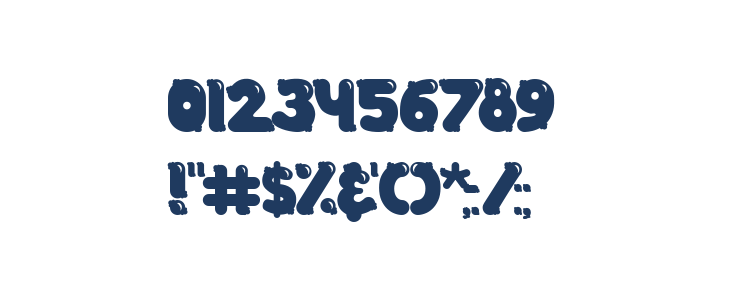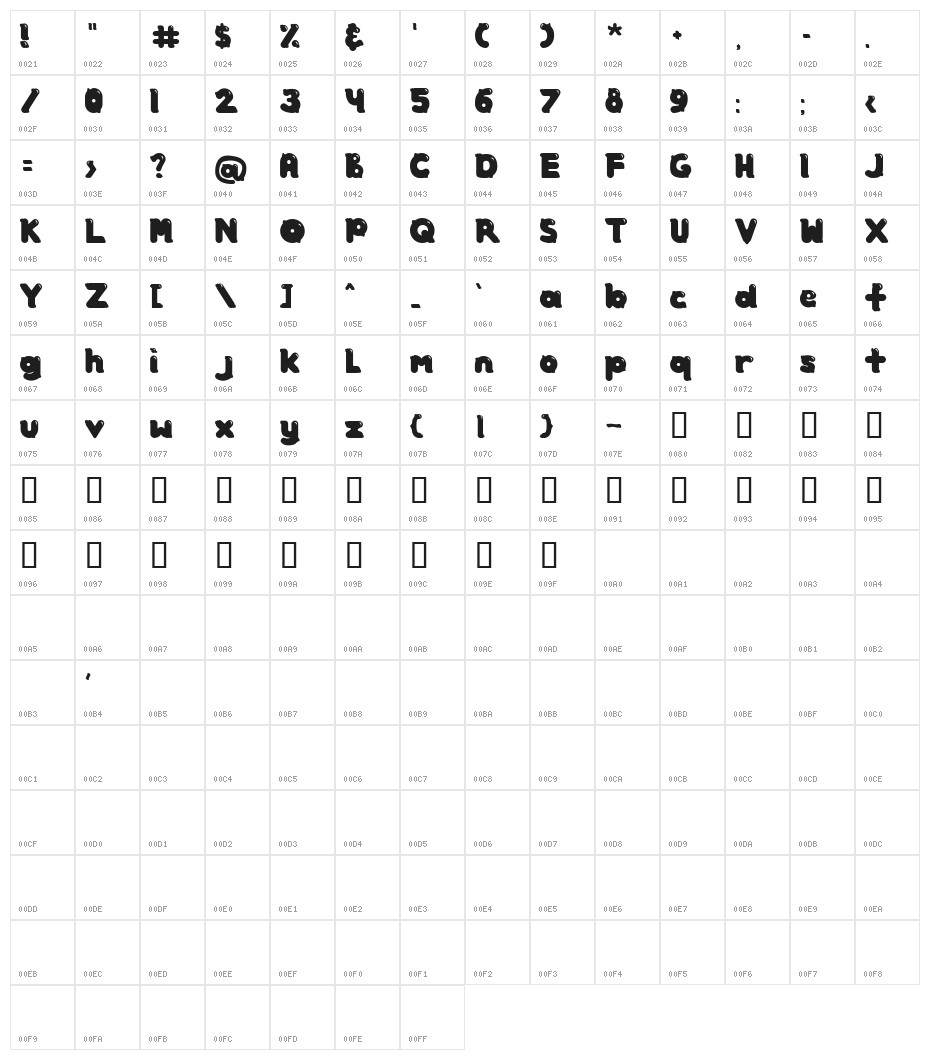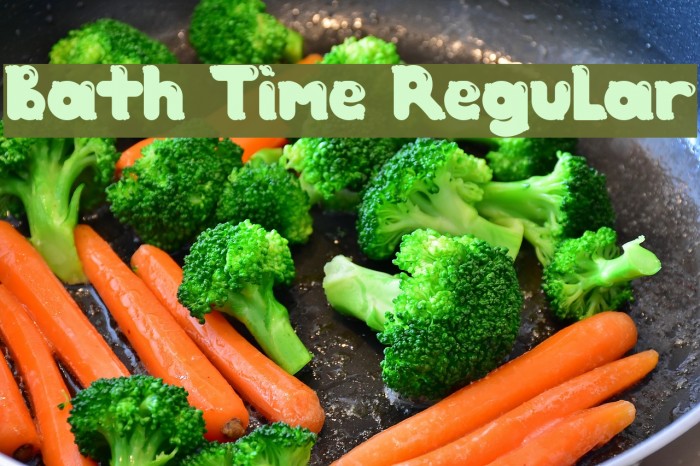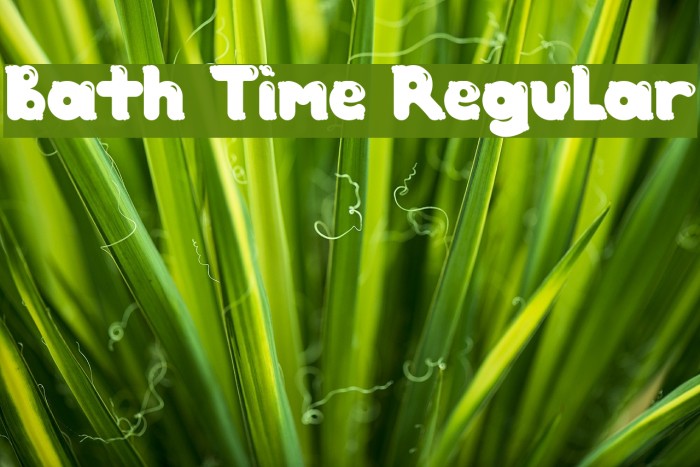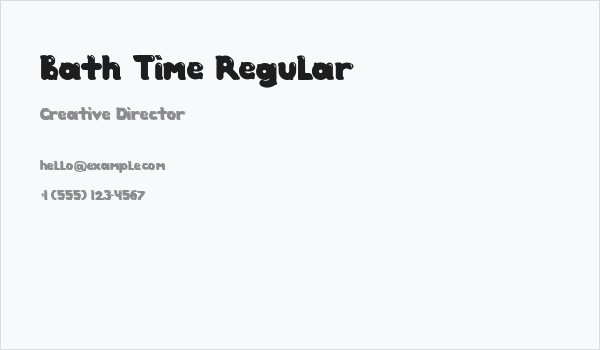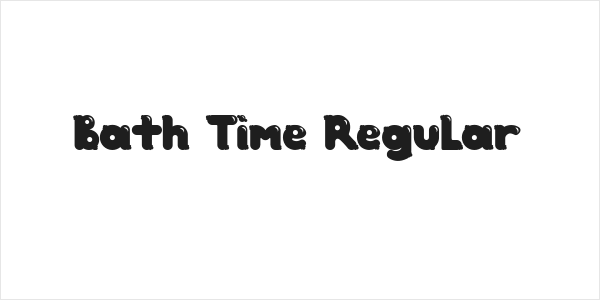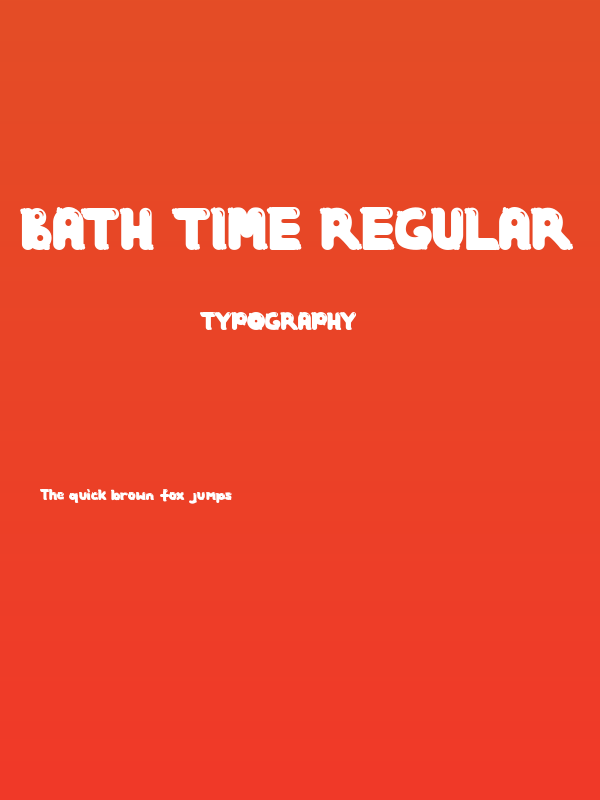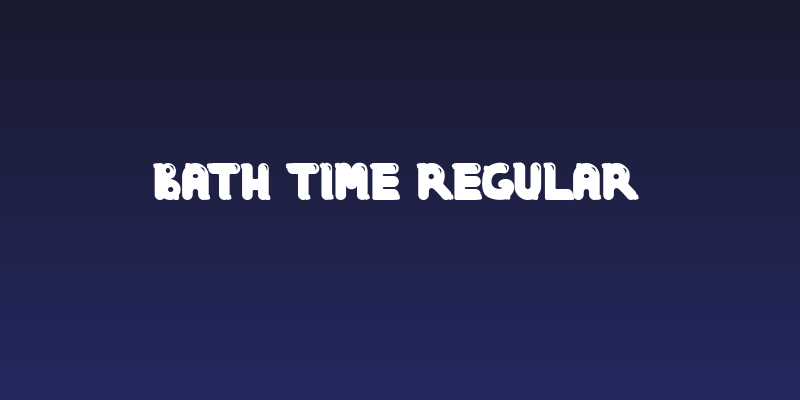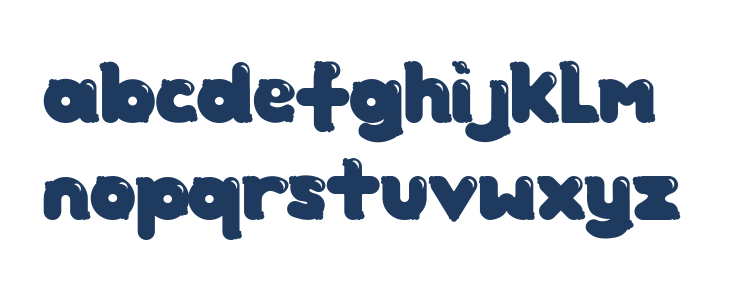
Bath Time Regular Font
✎ bubble letter
| 整体风格 | Playful, Whimsical |
| 推荐项目 | Ideal for children's books, playful branding, party invitations, and any project needing a fun, approachable aesthetic. |